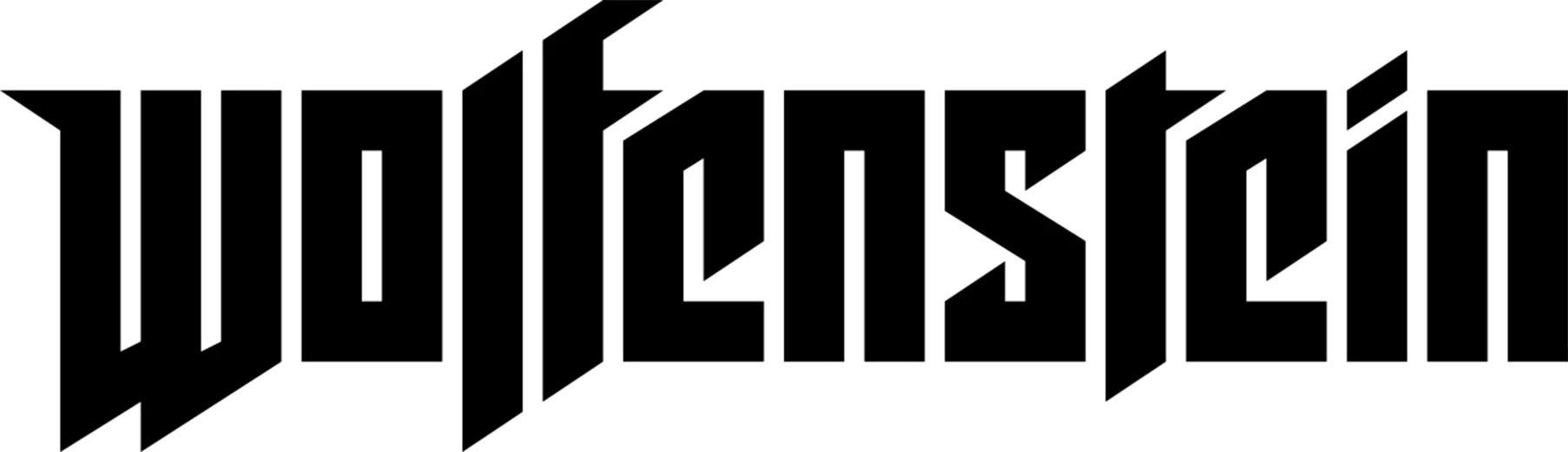
Wolfenstein Font - Wolfenstein Font
Wolfenstein Font
2 Farklı yazı karakteri bulunmaktadır. Birbirine çok benzerler biri büyük diğeri küçük harfler için idealdir.
Wolfenstein.ttf Ağustos 2009 tarihinde d3Xter tarafından CorelDRAW ve FontCreator programları ile 56 saatte tasarlanmıştır. Wolfenstein serisinin...